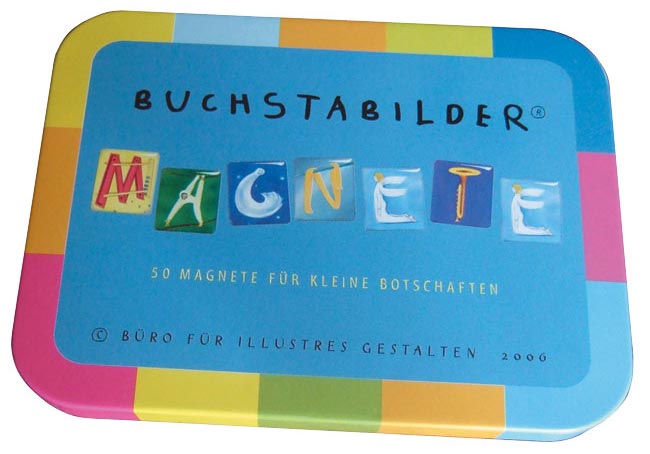
Die Buchstabilder des Büro für illustres Gestalten gibt es seit 2004 und wurden ursprünglich für den spielerischen Kontakt mit dem Alphabet entworfen. Sie zeigen alle Lettern in figürlicher Darstellung: Gegenstände sind so gemalt, dass sie die Form ihres Anfangsbuchstaben bilden. Die formale Verschmelzung von Buchstabe und Figur ist nicht nur eine Basis für das schnelle Lesenlernen, sondern auch schön anzusehen. Aus diesem Grund gibt es inzwischen eine Serie von Buchstabilder-Produkten, unter anderem die heute angebotenen Magnete.